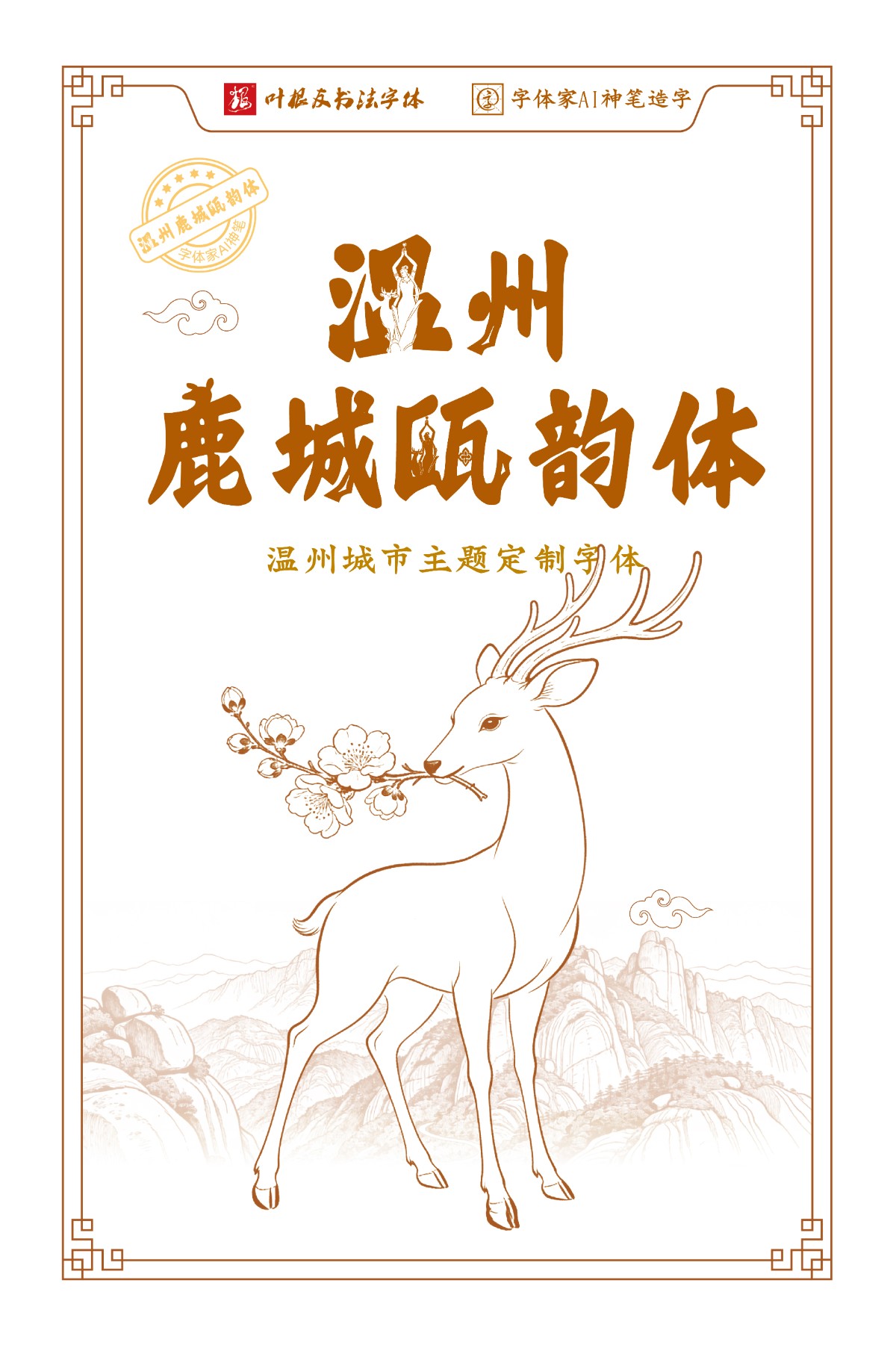
温州鹿城瓯韵体
字体是文化的载体,是城市的印记。今天,温州鹿城瓯韵体正式上线!这款字体由叶根友先生原创研发,融合瓯越文化底蕴与书法艺术,兼具瓯越文化特色与现代审美,将广泛应用于影视、文创、宣传等领域,成为鹿城文化传播的专属符号!下面请大家通过观看“温州鹿城瓯韵体”宣传片了解其独特的文化魅力。该字体版权归属温州市鹿城区互联网发展促进会所有,保留一切权力,如需转载发布本字体请务必注明该页字体出处超链接,否则视为违规发布。
“温州鹿城瓯韵体”是一款书写很新颖的字体,字体大方,适合各种设计作品使用!欢迎下载!